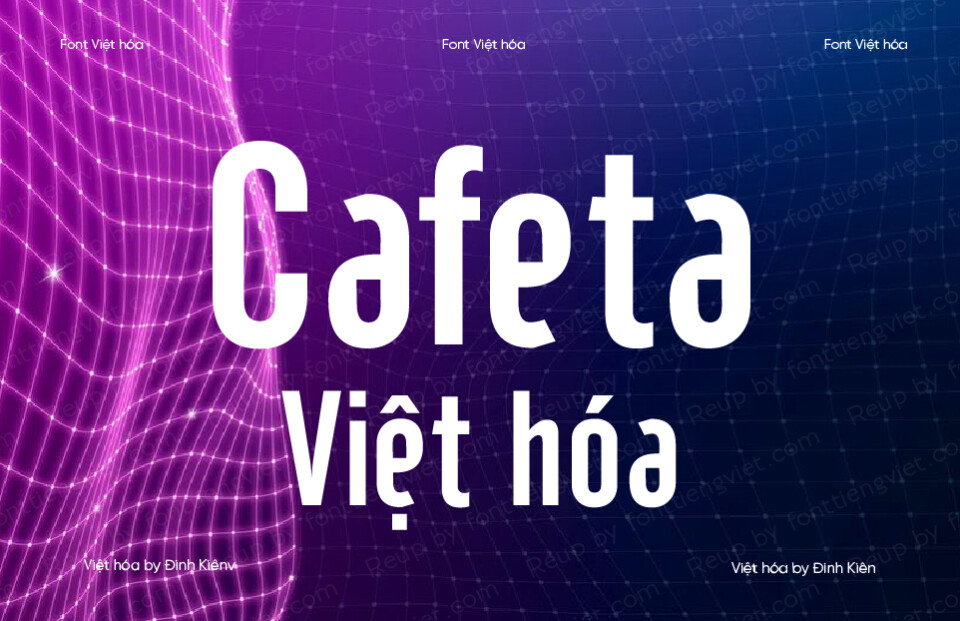
Khám Phá Font Việt hóa UTM Cafeta – Sự Lựa Chọn Hoàn Hảo Cho Học Sinh và Nhà Thiết Kế
Trong thời đại kỹ thuật số, việc trình bày thông tin một cách rõ ràng và chuyên nghiệp là yếu tố then chốt, đặc biệt đối với học sinh, sinh viên và các nhà thiết kế đồ họa. Sự lựa chọn về Font Chữ đóng vai trò quan trọng trong việc truyền tải nội dung, từ các bài tiểu luận, đồ án tốt nghiệp cho đến các ấn phẩm truyền thông. Giữa vô vàn lựa chọn font chữ trên thị trường, bộ sưu tập UTM của nhà thiết kế Lê Quốc Hùng luôn nổi bật với chất lượng cao và khả năng hỗ trợ tiếng Việt hoàn hảo. Trong số đó, Font Việt hóa UTM Cafeta đã nhanh chóng trở thành một cái tên được săn đón nhờ sự kết hợp giữa tính thẩm mỹ hiện đại và độ dễ đọc vượt trội. Bài viết này sẽ đi sâu vào lý do tại sao bộ font này lại trở nên phổ biến và cách tối ưu hóa nó cho các mục đích học tập và sáng tạo.
Tại Sao Font Việt hóa UTM Cafeta Lại Được Ưa Chuộng Trong Giáo Dục và Thiết Kế?
UTM Cafeta thuộc nhóm font chữ không chân (sans-serif), một kiểu chữ được giới chuyên môn đánh giá cao về khả năng hiển thị rõ ràng trên cả màn hình kỹ thuật số và tài liệu in ấn. Đặc điểm này khiến nó trở thành lựa chọn lý tưởng cho môi trường học thuật, nơi yêu cầu sự chính xác và dễ tiếp cận thông tin. Phiên bản Việt hóa của UTM Cafeta không chỉ giữ nguyên được vẻ đẹp thanh lịch, hiện đại của bản gốc mà còn được bổ sung đầy đủ các ký tự tiếng Việt, dấu thanh, và các ký hiệu đặc biệt, đảm bảo tính thống nhất về mặt typography khi sử dụng trong các văn bản phức tạp như luận văn, sách giáo khoa hoặc tài liệu ôn thi tốt nghiệp.
Đối với học sinh và sinh viên, việc sử dụng một font chữ đẹp và chuẩn mực như UTM Cafeta giúp nâng cao chất lượng trình bày của bài thuyết trình, báo cáo nghiên cứu. Một bản in luận văn sử dụng font chữ rõ ràng, bố cục gọn gàng sẽ tạo ấn tượng tốt hơn rất nhiều đối với hội đồng chấm thi. Đây không chỉ là vấn đề thẩm mỹ mà còn là sự tôn trọng đối với người đọc. Hơn nữa, những người làm công tác biên soạn tài liệu, giáo viên có thể dùng font này để tạo ra các bài giảng, đề thi chất lượng cao, giúp học sinh dễ dàng tập trung và tiếp thu kiến thức hơn.
Ưu Điểm Tuyệt Vời Của Bộ Font UTM Cafeta Đối Với Học Sinh, Sinh Viên
Việc lựa chọn một font chữ phù hợp có thể ảnh hưởng đáng kể đến hiệu quả công việc và học tập. UTM Cafeta mang lại nhiều lợi ích thiết thực cho cộng đồng học sinh, sinh viên và những người chuẩn bị cho các kỳ thi quan trọng, như kỳ thi trung học phổ thông quốc gia hoặc thi đại học.
- Khả năng Đọc Tối Ưu: Là font sans-serif, UTM Cafeta giảm thiểu mỏi mắt khi đọc trong thời gian dài, một yếu tố cực kỳ quan trọng khi học sinh phải tiếp xúc với tài liệu ôn tập dày đặc.
- Tính Chuyên Nghiệp Cao: Font chữ này được thiết kế với độ dày nét ổn định và khoảng cách chữ hợp lý, mang lại vẻ ngoài chuyên nghiệp, phù hợp để in ấn các tài liệu chính thức, chẳng hạn như chứng chỉ, hồ sơ du học hoặc các dự án nghiên cứu khoa học.
- Hỗ Trợ Tiếng Việt Toàn Diện: Đây là ưu điểm lớn nhất của các font Việt hóa UTM. Mọi ký tự tiếng Việt đều được căn chỉnh một cách tinh tế, không bị lỗi mất dấu hay lệch dấu như nhiều font quốc tế khác. Điều này giúp các văn bản tiếng Việt của bạn luôn hoàn hảo về mặt ngôn ngữ học.
Lưu Ý Quan Trọng Khi Dùng Font UTM Cafeta Trong Môi Trường Học Thuật
Việc kết hợp UTM Cafeta với các font chữ khác cũng cần được thực hiện một cách cẩn thận để giữ gìn tính thẩm mỹ tổng thể. Ví dụ, UTM Cafeta là font tiêu đề hoặc font nội dung rất tốt. Nếu cần một font chữ khác để nhấn mạnh hoặc tạo điểm nhấn, hãy chọn các font tương phản nhưng vẫn hài hòa, ví dụ như một font script nhẹ nhàng cho chữ ký hoặc trích dẫn, hoặc sử dụng các biến thể (bold, italic) của chính UTM Cafeta để tăng cường hiệu quả thị giác mà không làm mất đi tính đồng nhất của tài liệu. Việc làm chủ typography này sẽ giúp các bài báo cáo và đồ án của bạn trở nên chuyên nghiệp hơn bao giờ hết.
Tóm lại, Font Việt hóa UTM Cafeta là một tài sản quý giá cho bất kỳ ai đang tìm kiếm một giải pháp typography chất lượng cao, rõ ràng và hỗ trợ tiếng Việt hoàn hảo. Từ việc biên soạn tài liệu giảng dạy, thiết kế đồ họa cơ bản cho đến việc hoàn thiện những bài luận văn tốt nghiệp quan trọng, UTM Cafeta đều đáp ứng xuất sắc mọi nhu cầu. Việc đầu tư thời gian để tìm hiểu và sử dụng thành thạo bộ font này chắc chắn sẽ mang lại lợi thế lớn trong học tập và công việc. Hãy tải và trải nghiệm ngay để thấy sự khác biệt mà bộ Font Chữ tuyệt vời này mang lại cho các dự án của bạn.